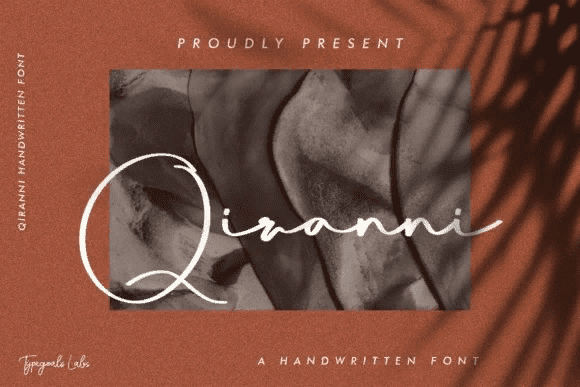
[Creativefabrica] Qiranni Font (2021)
Название: Qiranni Font (2021)
[Creativefabrica] Qiranni Font (2021)
Qiranni
- это нежный, элегантный и плавный рукописный шрифт.
Он имеет красивые и хорошо сбалансированные символы, которые могут улучшить внешний вид самых разных проектов, от упаковки продуктов до визитных карточек и многого другого!